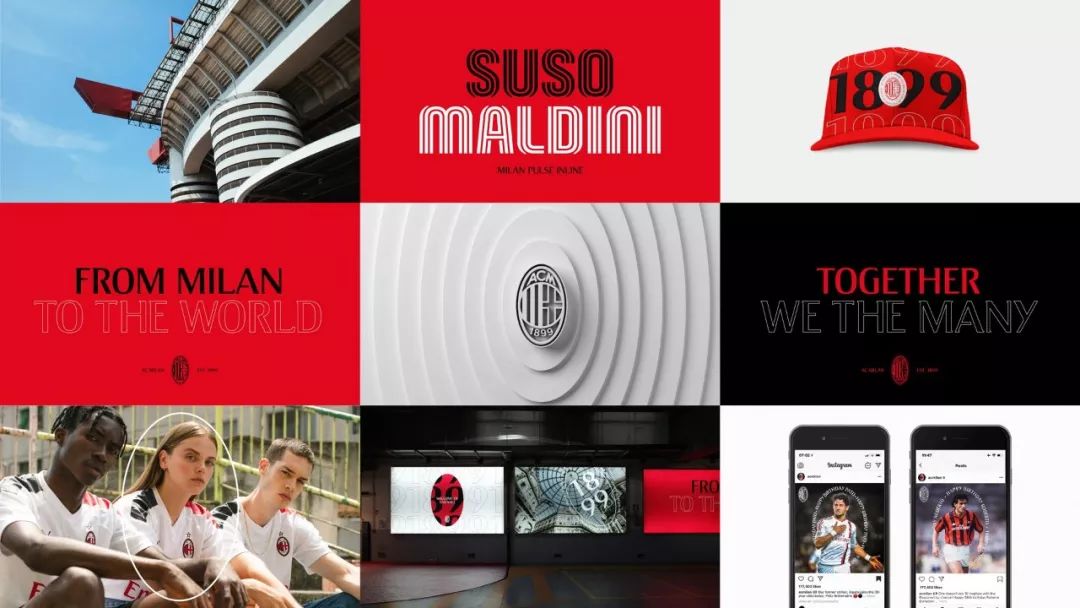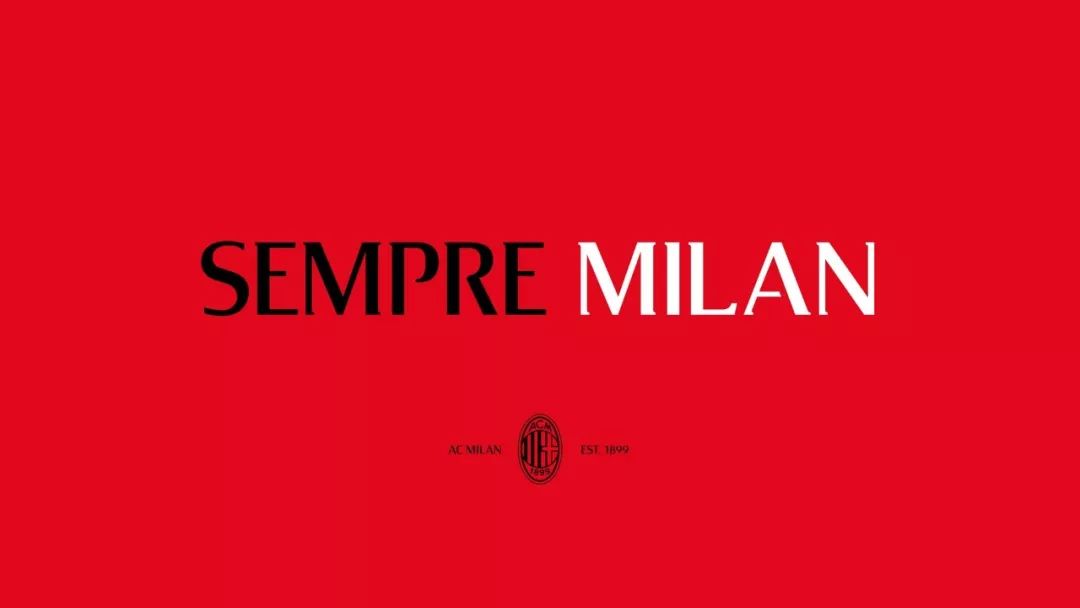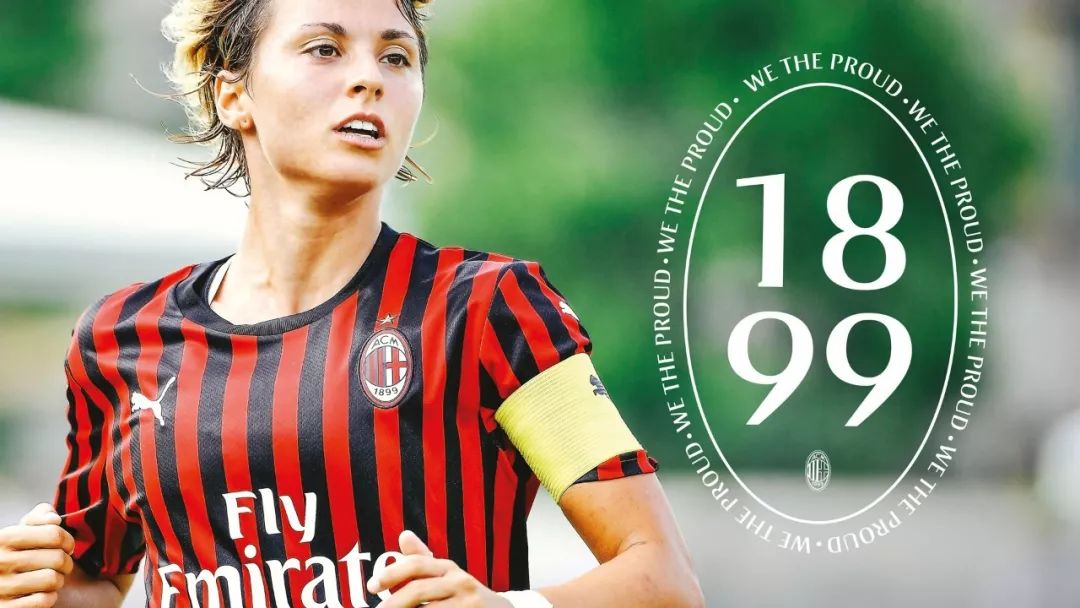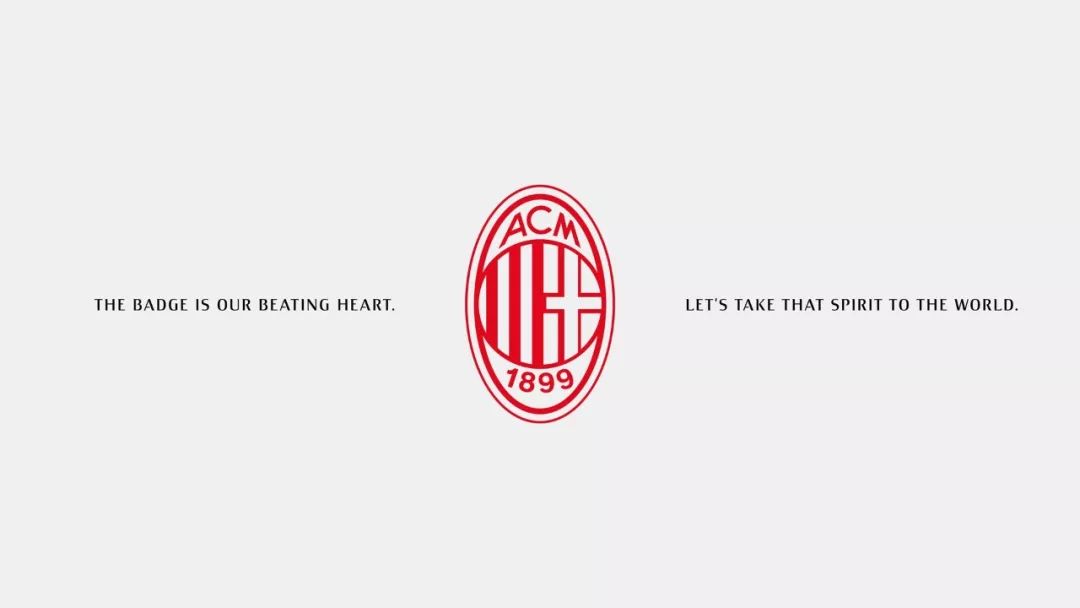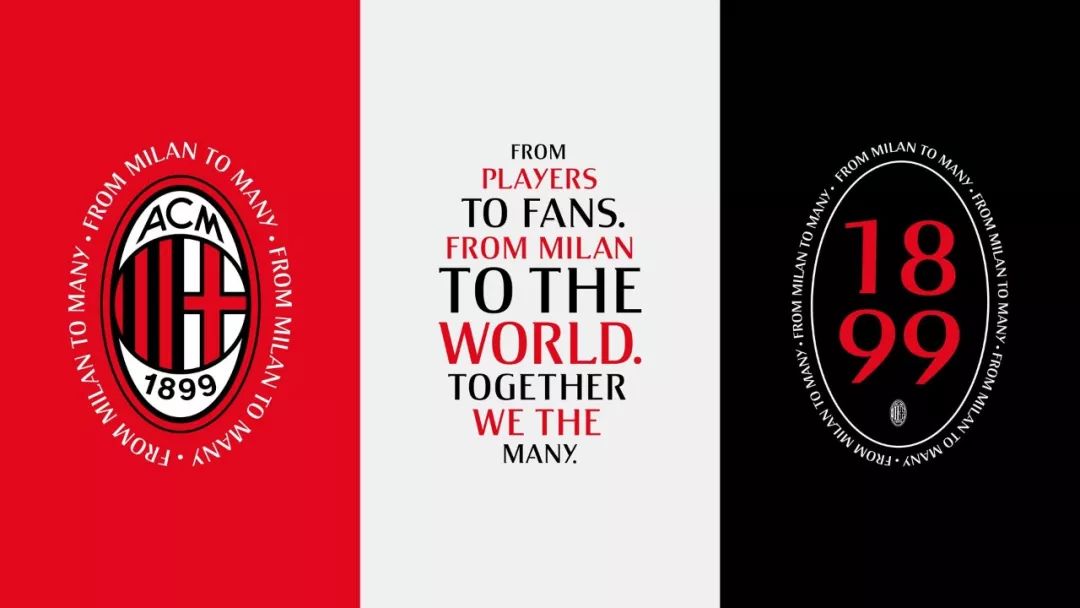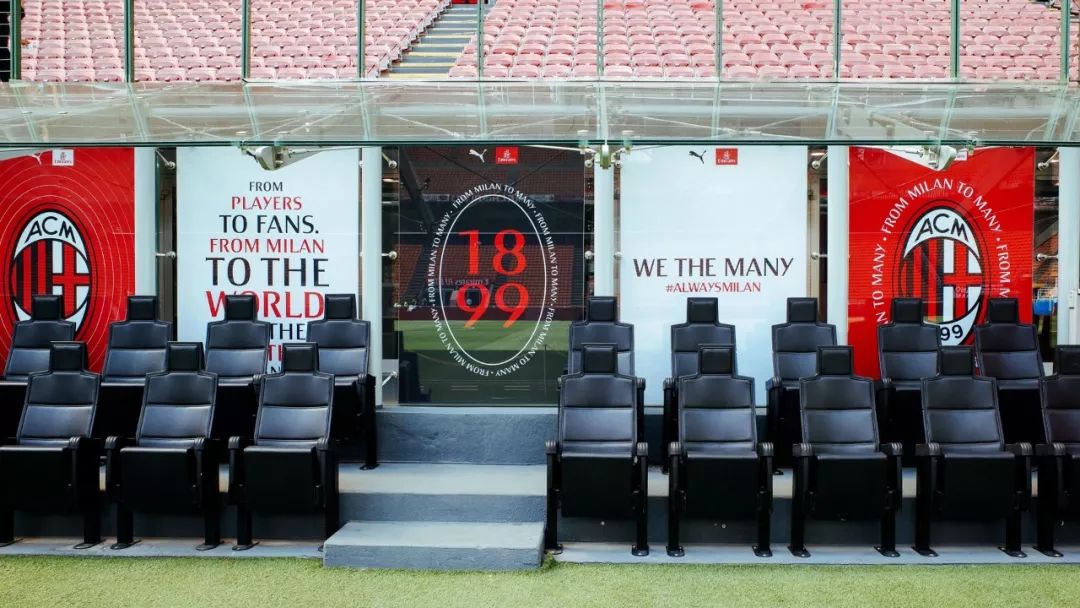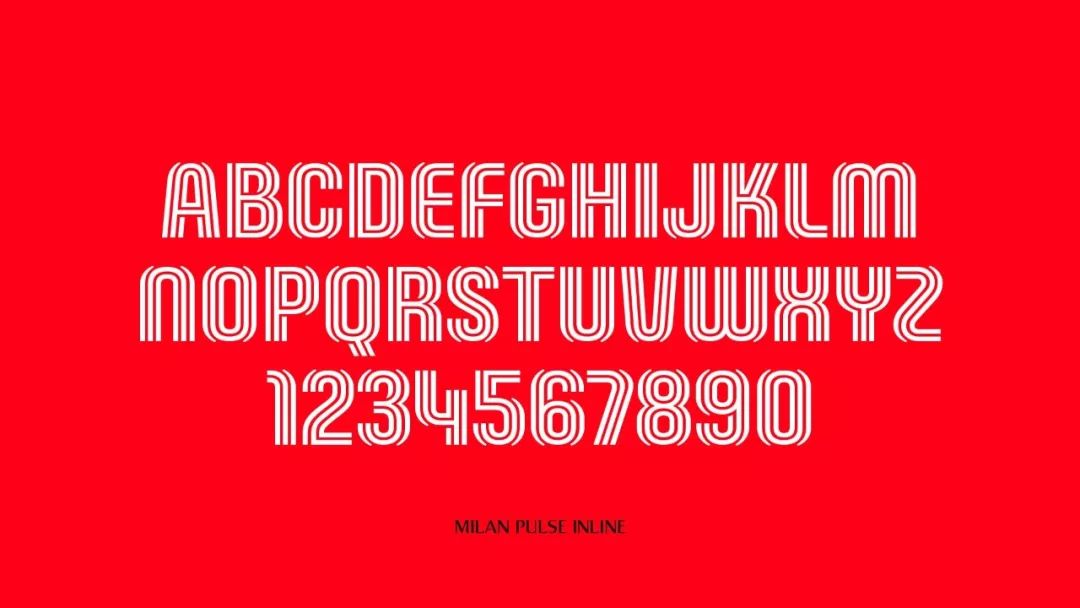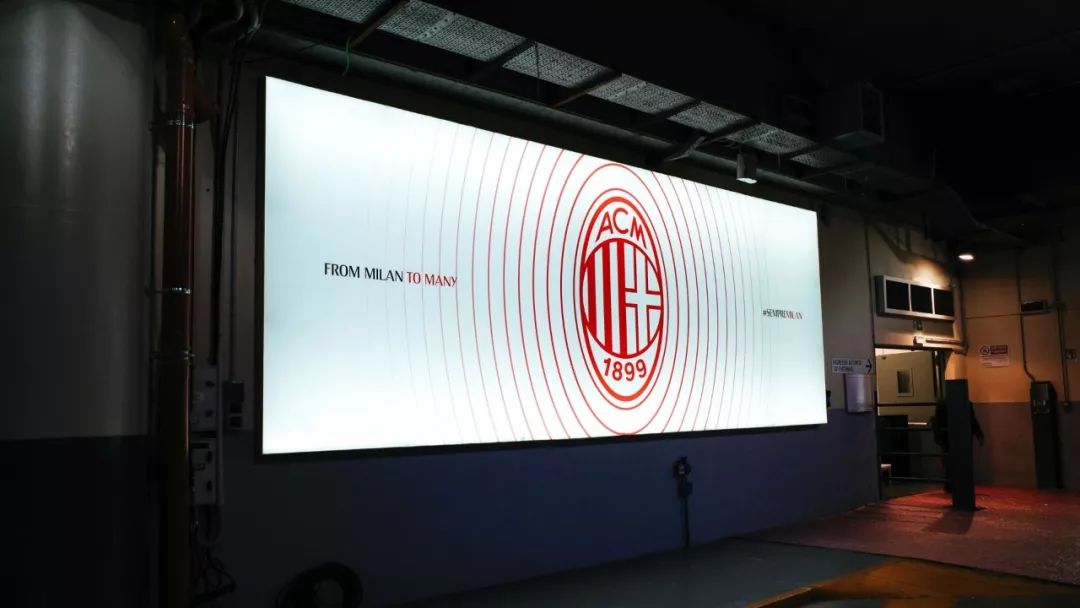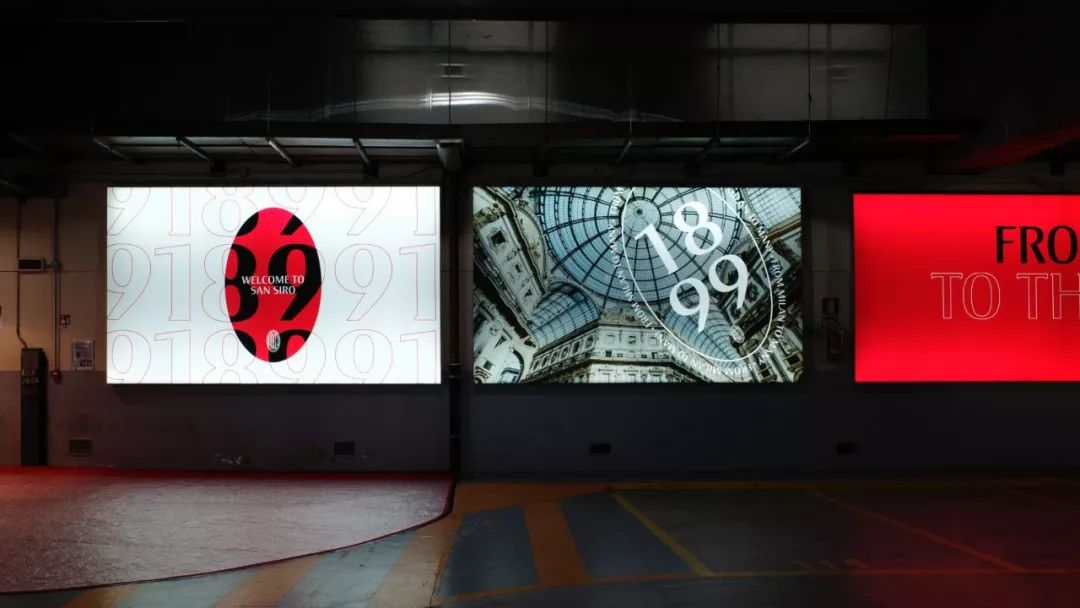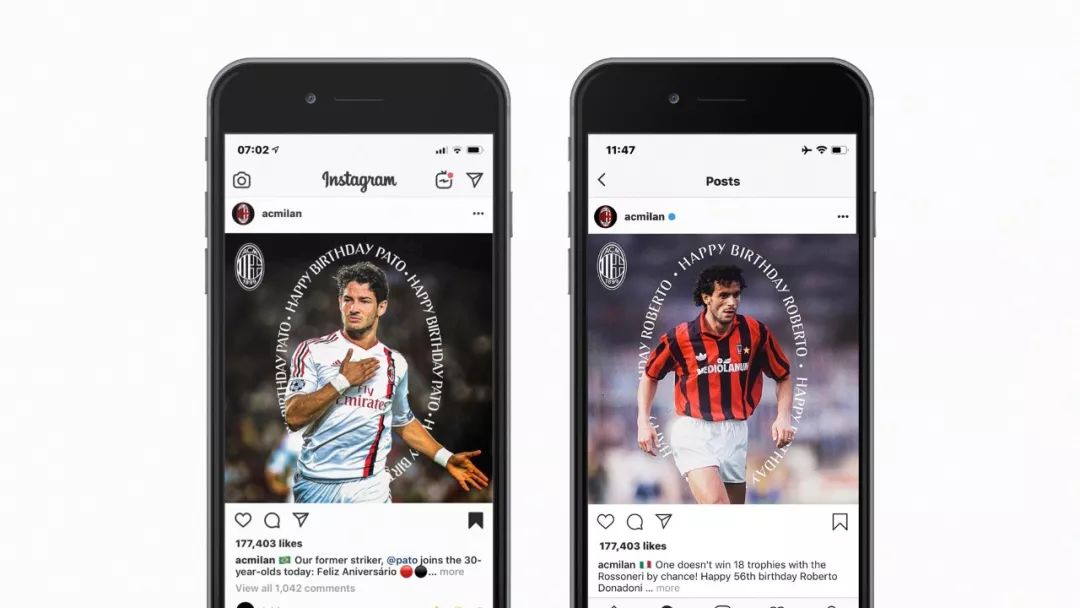
120岁了!AC米兰公布了全新品牌设计!
2019年9月16日,意大利米兰——欧洲足球豪门AC米兰宣布正式启用全新视觉识别系统,并从2019/20赛季起开始使用,这也标志着AC米兰俱乐部与全球范围内的拥趸将迎来崭新的时代。
AC米兰足球俱乐部,成立于1899年12月16日,一群聚集在杜诺德(Dunawd)宾馆房间里的球迷成立了一家体育俱乐部—米兰板球和足球俱乐部,创始人为阿尔弗雷德·爱德华兹。
作为一支拥有120年辉煌历史的俱乐部,AC米兰此次委托伦敦的设计代理公司DixonBaxi进行大胆的创新挑战。
希望将全球最具标志性的足球俱乐部形象升级并转化为生活方式类品牌,但同时保留俱乐部的本质以及体育对人们的意义。
为辉煌的历史所感染,专注于未来创造荣耀——被这样的信念所启发,DixonBaxi的设计灵感以俱乐部的核心价值观——团队合作,卓越,激情和优雅为基础,为新一代充满个性又自豪的罗森内里们设计了AC米兰的全新视觉体系。
“Sempre Milan 忠生米兰”
为了确保这套视觉尽可能地保留俱乐部最真实的风格,他们将俱乐部最具标志性的队徽作为创意核心,这也象征着从米兰到全世界,4.5亿米兰球迷共同的心跳。
这样的精神被DixonBaxi囊括为一句简单的口号:忠生米兰(Sempre Milan),用“椭圆的力量”体现俱乐部的核心价值并强调俱乐部的意大利传统。
无论身在何处,这句口号都能让自豪的罗森内里们团结一心,振臂高呼。
与此同时,俱乐部还将以现代化的方式重新打造摄影风格,捕捉俱乐部球员与球迷们的激情,让观看者能够沉浸其中。
俱乐部还决定为定制字体注入新的活力,灵感来源于球队粉丝的“共同心跳”,这款字体将与现有AC米兰的字体共存。
全新的品牌视觉将体现在俱乐部的所有对外交流方式上,从数字平台、票务与电子商务,到俱乐部工作区域、一线队形象、赞助商与各种地点——圣西罗体育场、米兰之家、米兰内洛与维斯马拉体育中心,同时还会呈现在周边商品与体育场图像上。
DixonBaxi联合创始人兼创意总监阿波瓦·巴希(Aporva Baxi)表示:“AC米兰是全世界最具代表性的足球俱乐部之一。
但除了俱乐部的规模与历史之外,我们更被这个项目的大胆无畏精神所吸引。接手全世界最著名的体育品牌之一,并向更加现代化和国际化的大众重新诠释。
全新品牌的形象将在极大范围内被使用——仅仅是圣西罗就有超过1000种不同的品牌元素需要考虑。
我们很清楚地知道我们想讲述一个故事,其中包括历史上那些身披红黑战袍的传奇球员,球队赢得的奖杯与荣誉,潜力新星以及未来的成就。
这次品牌重塑让这个超过100年历史的俱乐部有了全新的视角,并开始思考下一个世纪对于俱乐部意味着什么。
整个过程中我们与AC米兰的团队合作无间,我迫不及待地想在现实世界中看到这一新的品牌形象。”